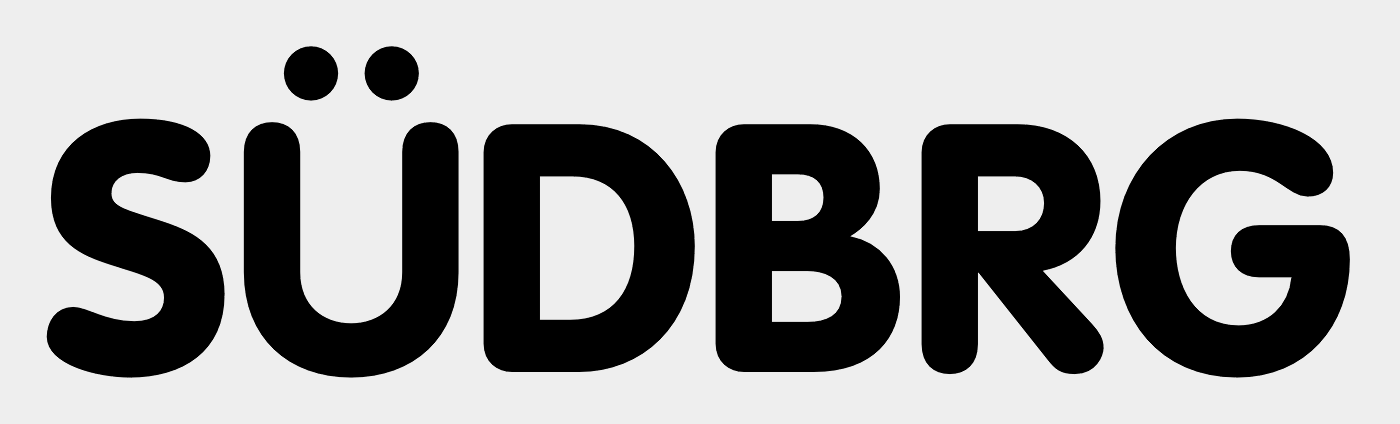
Suche Schriftart Busunternehmen 1990er Jahre
Wende mich hier an euch, da ich diese Schrifart suche.
das sollte in etwa eine gekippte VAG Rounded sein. Die VAG-Rounded ist in etwa eine rundgelutschte Futura und es gibt von der keine schiefen Schnitte.
Leider kenne ich keine freie Version der VAG-Rounded und die Black (Megafette) habe ich hier nur in einem alten Paket von Schriften von einen HP-Drucker. Aber schau mal auf den diversen Freefontseiten nach dem Tag oder der Kategorie Rounded. Vielleicht findest Du eine ausreichend ähnliche Schrift.